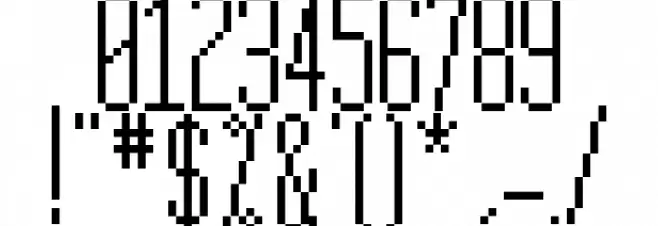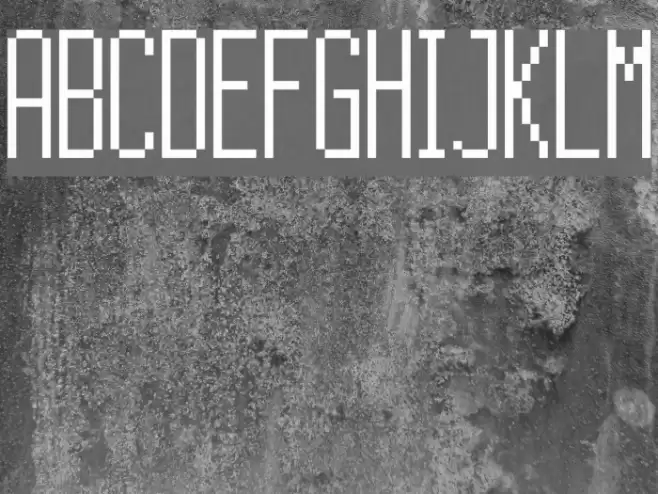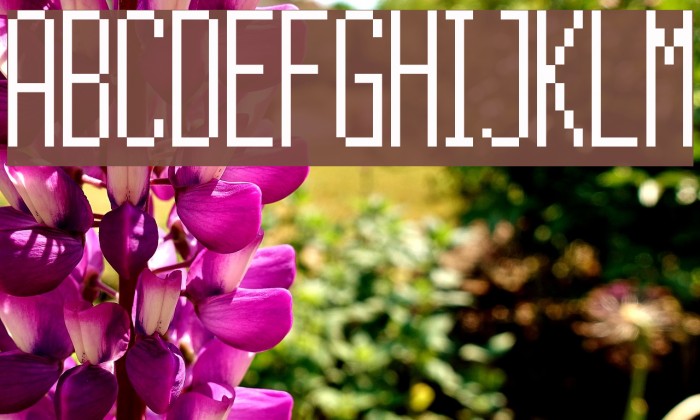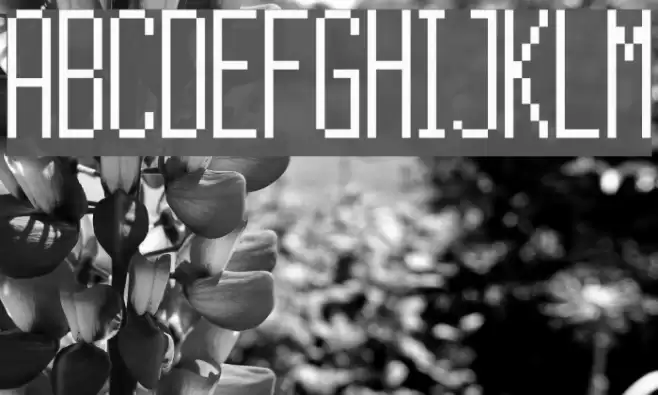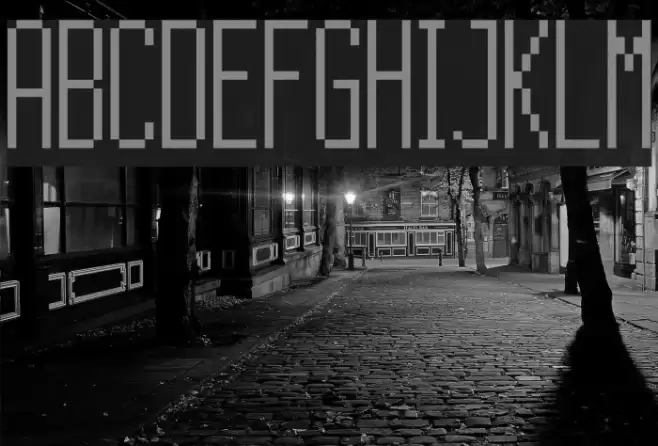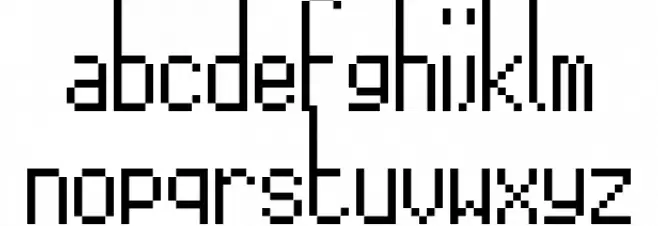
15x5 Regular Font
| Caz de utilizare | Logos, Headlines, Digital displays |
| Proiecte propuse | Ideal for retro video games, digital art projects, tech-themed posters, and any design requiring a vintage computer look. |